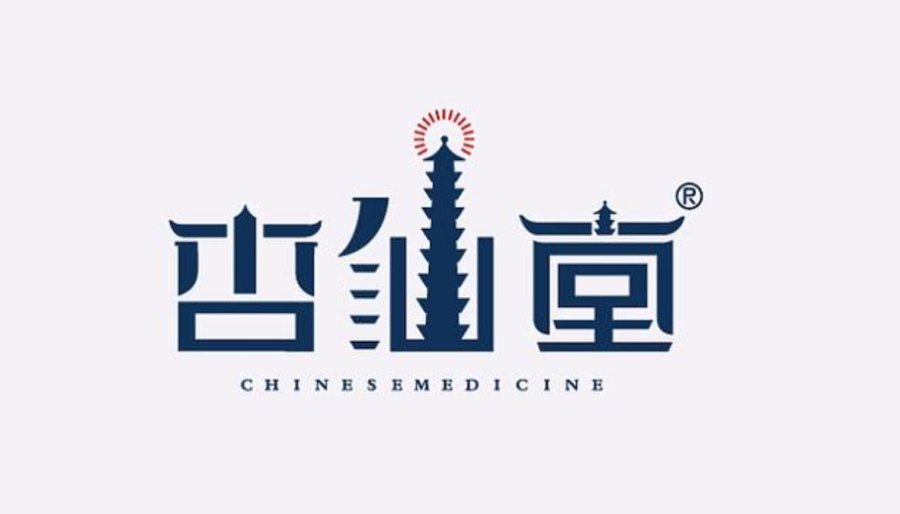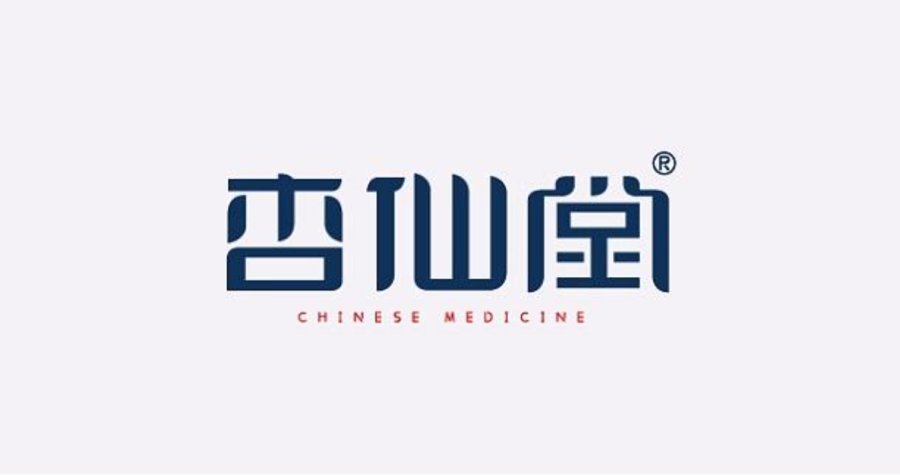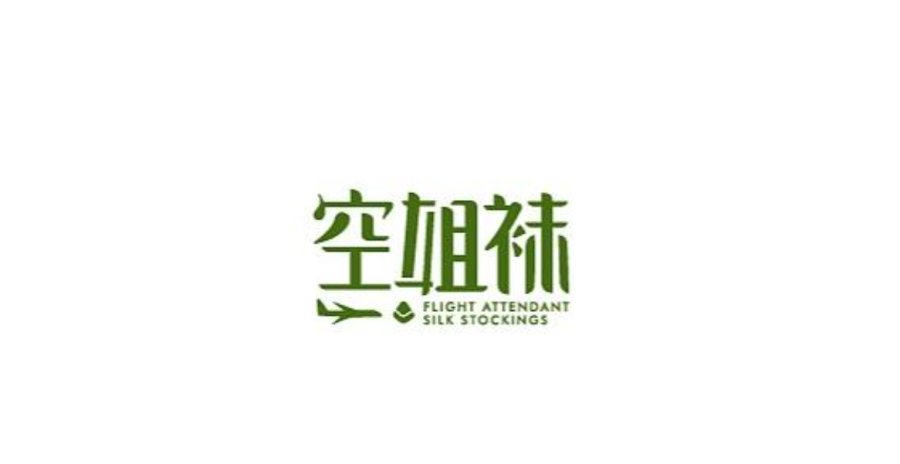
愉快搬砖!终于有了一款可能啥也不用改就能做logo的字体了。
站酷小薇LOGO体是李大卫送给自己女儿出生三周年的一个礼物。其目的是为了填补免费字体中的LOGO体空缺。字体笔画浑厚,识别性高,放大放小空间间隙都能如意灵通。这款字体撇和捺伸展流畅,模竖转折硬朗,工业设计感十足,线条流畅,结构简洁大方,伴有字体稍作变形,在结构上更有意思一点。
字体笔画浑厚视觉,识别性高,放大放小空间间隙都能如意灵通,字体设计大胆尝鲜,笔画简略了一些原本字体的造型,显得前卫,偏傍部首做了像字标LOGO类似的变形,增加了变形的趣味。字体四平八稳,字笔画与剑身相似,修长、谦和、美感丰富,放大缩小都能尽显平衡透气。
字体应用例子 by 上海佐兹设计公司